ダイナフォント30周年を記念した30枚の札による特別な「DynaFont版フォントかるた」
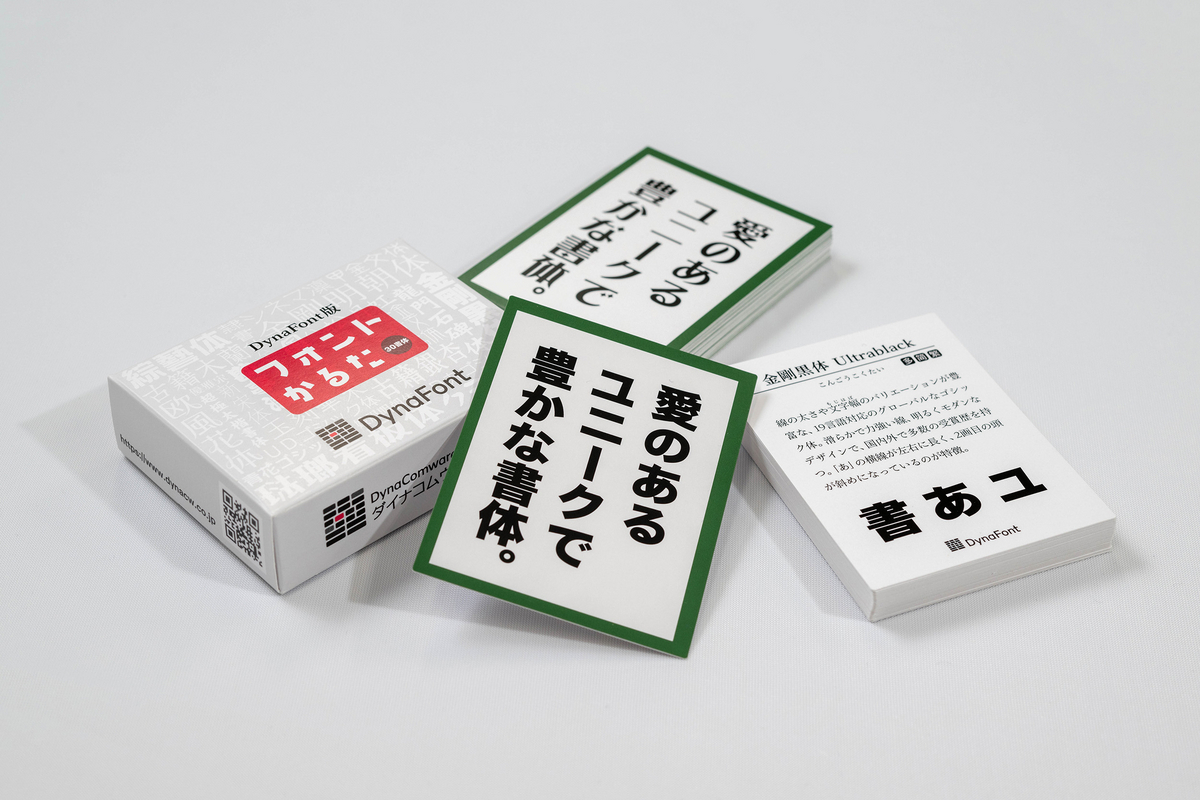
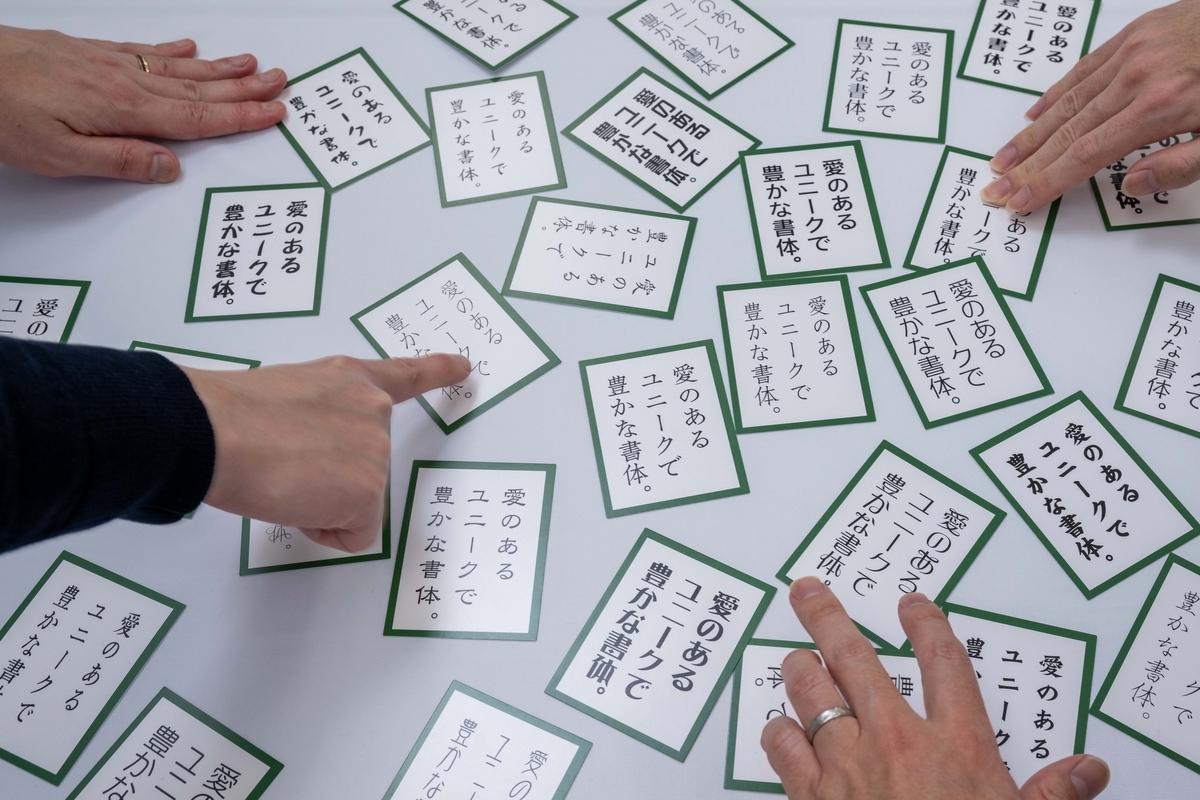
「フォントかるた」は、フォントかるた合同会社の制作・販売による、2017年の発売以来、本体と拡張パックのシリーズ累計販売数12,000部を超える大人気かるた。
読み上げられたフォント名と解説をヒントにしてそのフォントの札を取るというかるたゲームで、取り札に書かれた文言はすべて「愛のあるユニークで豊かな書体。」となるが、すべての札のフォントが異なり、文字の形の違いを見分けて取るというこれまでにないかるたとなる。
「DynaFont版フォントかるた」ではダイナフォント30周年にちなんで、ダイナフォントを代表する30書体を厳選して収録した。
有名作品などに使用されているお馴染みの人気書体から、2023年に発表された最新の書体まで幅広く網羅して文字の美しさから面白さ、多言語による多様性まで伝えた非売品のプレミアムな特注品「フォントかるた」となる。
フォントかるた制作チームによる「DynaFont版フォントかるた」完成コメント
私たちはフリーランスのデザイナー4人で活動をしている、フォントかるた制作チームです。このたびダイナコムウェアのみなさまと共同で「DynaFont版フォントかるた」を制作いたしました。DynaFontの30周年という記念のときに、また私たち自身も長年使わせていただいているDynaFontでフォントかるたを完成させられたことを、本当に嬉しく、また大変光栄に思っております。ぜひたくさんの方々に「DynaFont版フォントかるた」で遊んでいただき、DynaFontの歴史を感じる書体の深い味わいや、バラエティに富んだデザイン書体の楽しさを再発見していただけることを願っています。